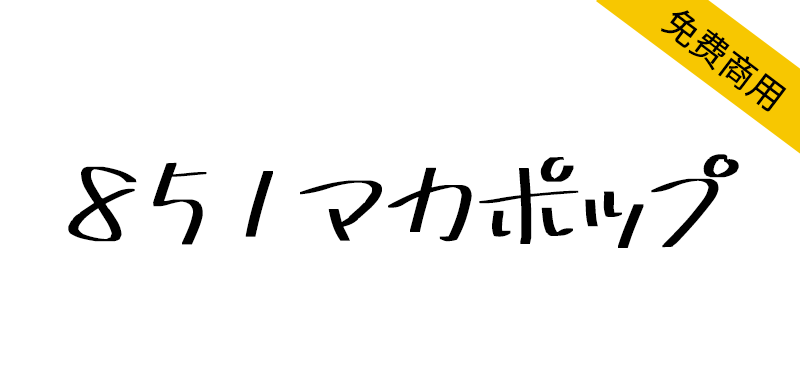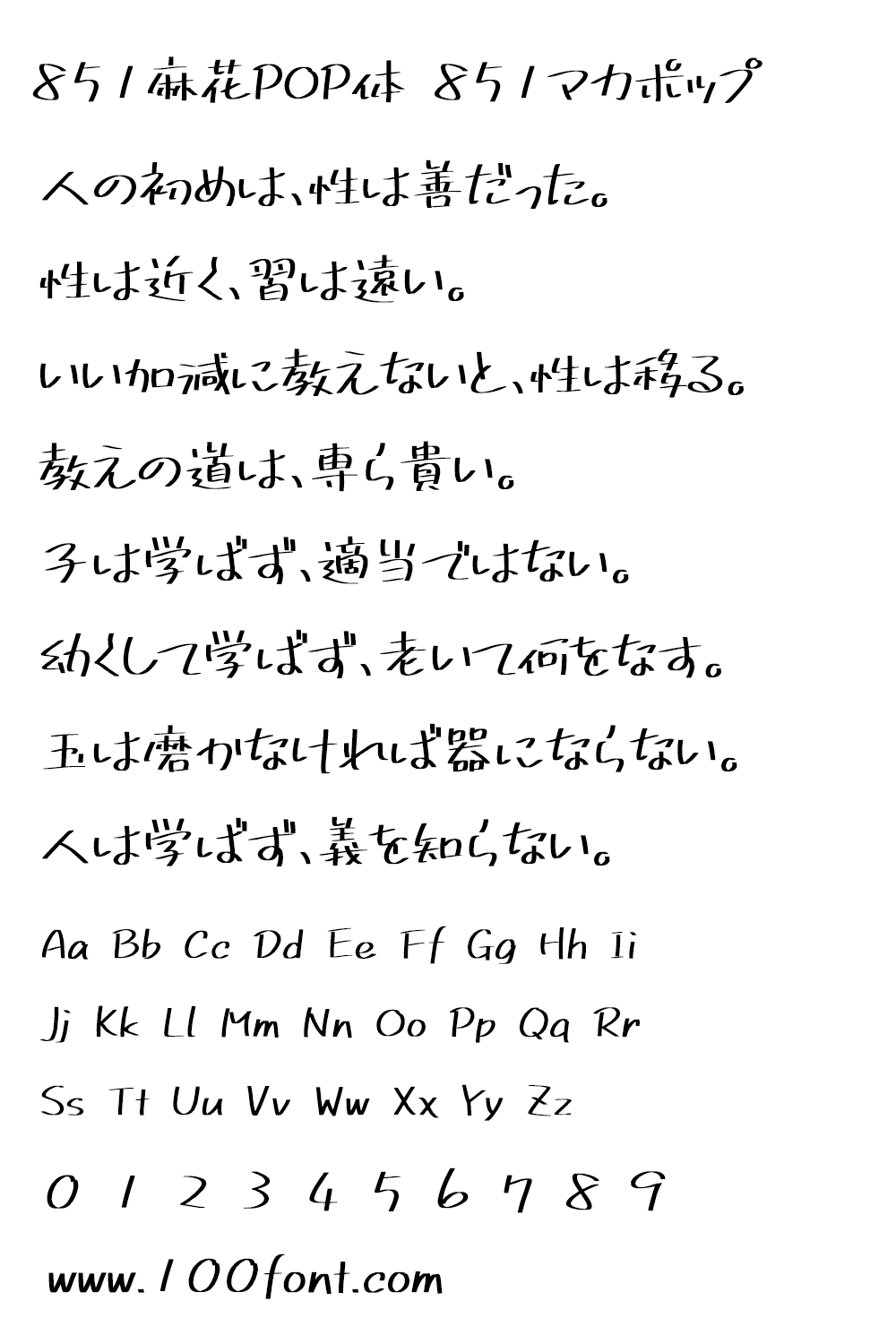
851麻花POP体(851マカポップ)是由日本设计师 8:51:22 pm设计的一款横粗的日文手写字体,当前字符数:9620个字符(不包括空格)。
对应文字:JIS X0208(Shift-JIS)的全部文字(全部JIS第1、第2水准汉字),Unicode“拉丁辅助”,JIS外汉字中可能有用途的数千个文字。
注意:这款字体适用于繁体和日文,不适用于简体中文,容易缺字。